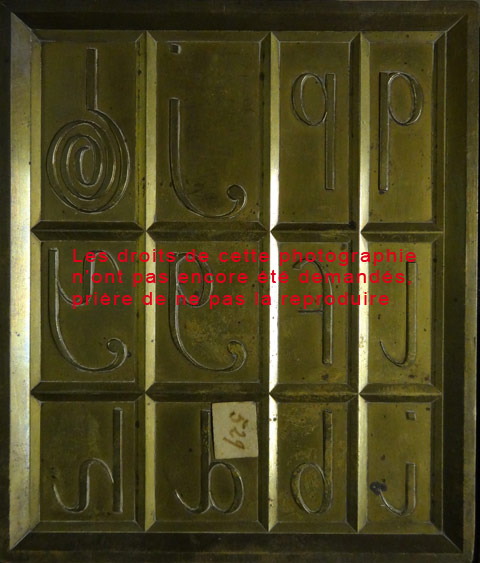
Bonjour ceux de la liste, encore besoin de vos lumières... Voici quelques jours nous sommes allés Jacques André et moi dans les réserves du musée du CNAM et nous sommes tombés en arrêt devant l'objet dont je joins la photo. C'est un moule qui nous vient de la fin du 18e siècle. On met de côté le fait qu'il montre des lettres à l'envers, il ne servait pas dans un processus d'impression mais de gaufrage. La question est : quel est ce signe à la gidouille préubique(*) situé en haut à gauche du moule ? Il n'est probablement pas dans la liste des signes unicode, du moins ne l'ai-je point vu... On peut penser à un point d'interrogation (tête en bas et sans son point) pour maniaque, à une cédille géante pour forcené, à une crosse épiscopale satanique... mais ce n'est sans aucun doute pas ça. :-) _______ (*) Ce moule précède de plus de 80 ans la naissance d'Ubu ; ubique : relatif à Ubu ≠ ubuesque : relatif au comportement d'Ubu. Christian Laucou